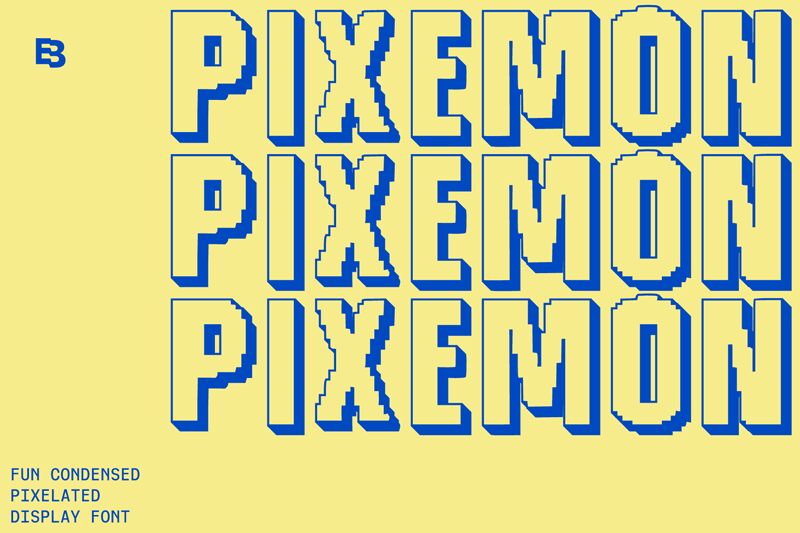
Pixemon, de Eko Bimantara, es una tipografía display 3D gratuita que destaca por sus imponentes mayúsculas muy compactas y sus profundas sombras desplazadas. Sus bordes escalonados e irregulares aportan a las caras anchas el gancho característico de los juegos arcade.
El cartel de videojuegos retro es su entorno ideal, ya que su profundidad maciza, su interletraje comprimido y sus contornos descentrados evocan las ilustraciones de las máquinas recreativas y los torneos de videojuegos sin vincular el diseño a una era concreta de consolas. Esa estructura de gran tamaño hace que los envases de aperitivos y el merchandising de estilo streetwear parezcan divertidos objetos gráficos; asimismo, en la señalética de gran formato para festivales, los planos laterales oscuros pasan a formar parte de la ilustración en lugar de interpretarse como un adorno independiente.